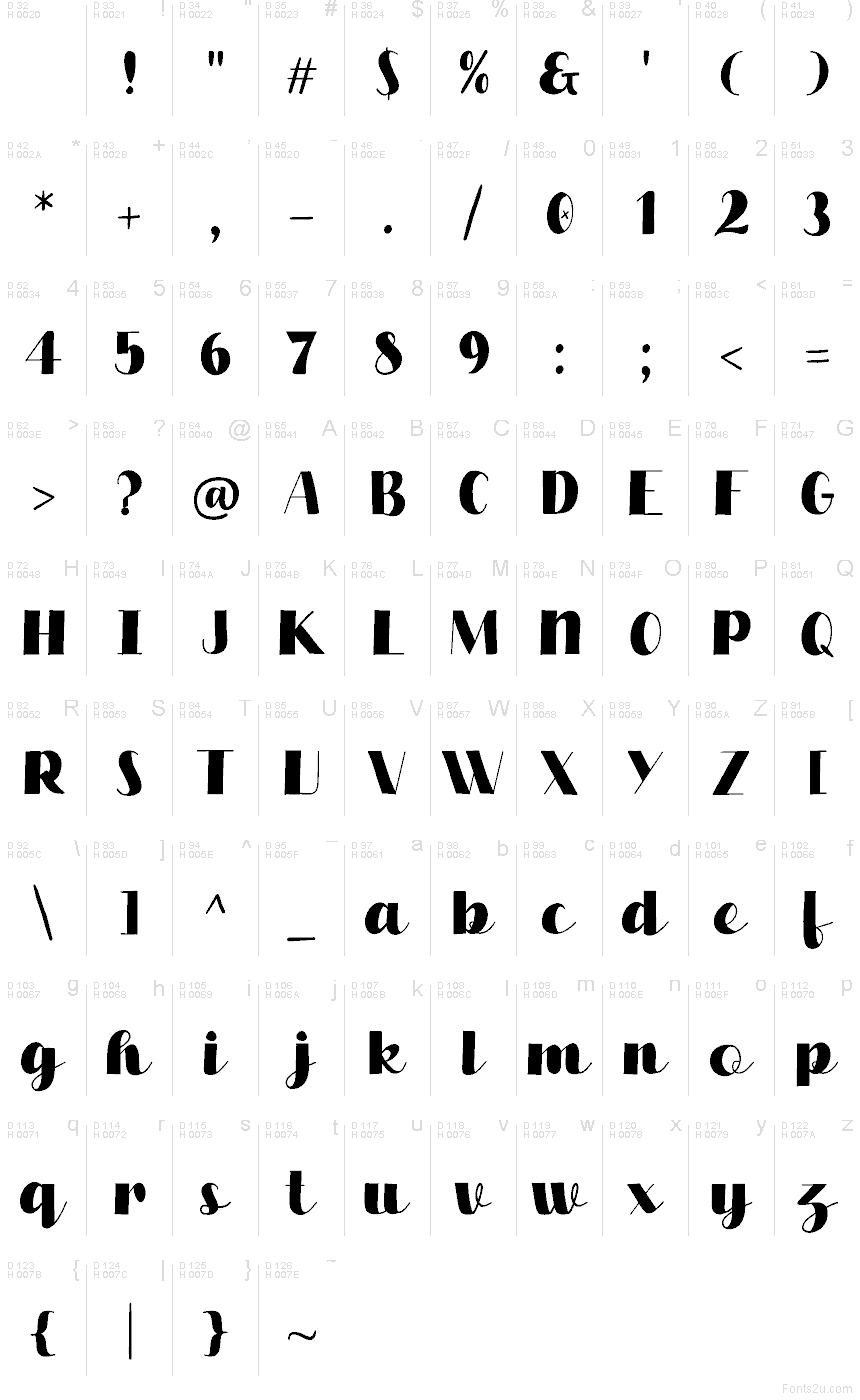
Kids Asia
Kids Asia від Hello Good Studio - це безкоштовний рукописний шрифт із широкими округлими формами. Завдяки живим деталям у накресленні він виглядає природно та зовсім не механічно. Поєднання впевнених вертикальних форм і м’яких вигинів надає йому справжнього «рукописного» ритму, що ідеально підходить для молодіжного та неформального дизайну.
Kids Asia чудово підійде для дитячих книг, навчальних матеріалів, запрошень, логотипів, пакування та плакатів, адже його форми виглядають невимушено, не втрачаючи при цьому структури. Цей безкоштовний шрифт також добре пасуватиме до яскравої графіки для соцмереж, етикеток товарів та грайливих редакційних заголовків, де потрібна рукописна стилістика, яка залишається чіткою та привабливою.